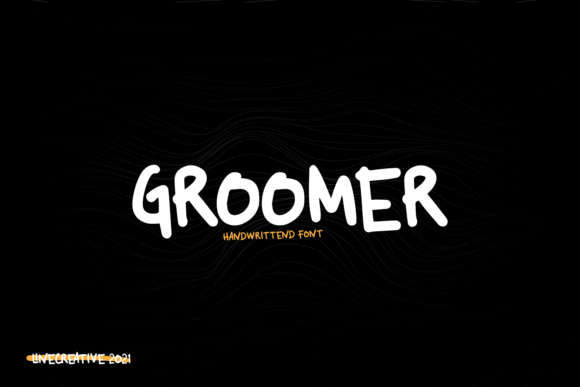
Грумер - это жирный и простой рукописный шрифт.
Этот шрифт идеально подходит для придания авантюрного и аутентичного вида вашей следующей дизайнерской идее!